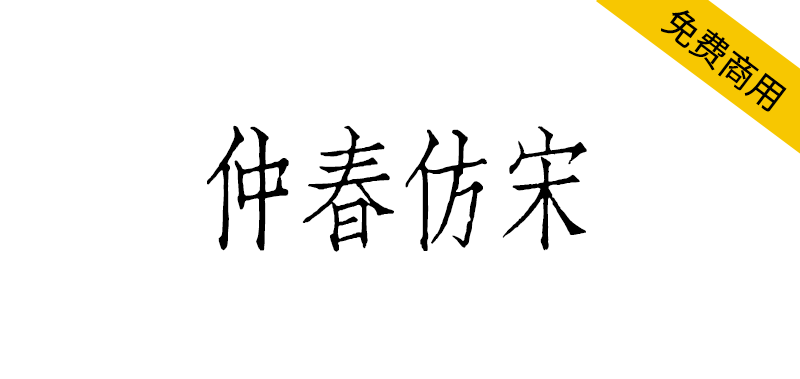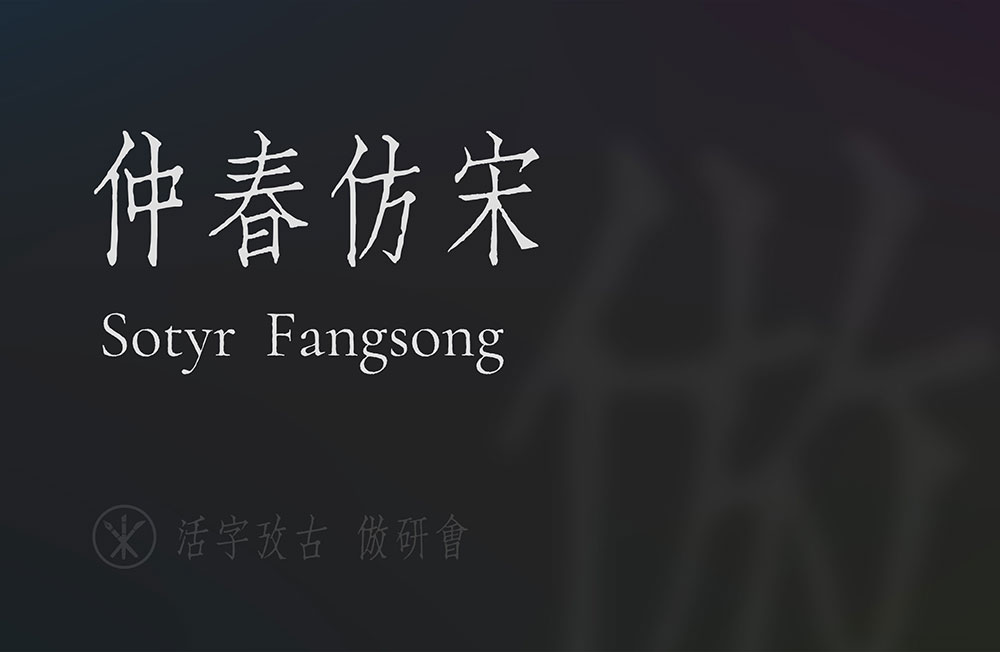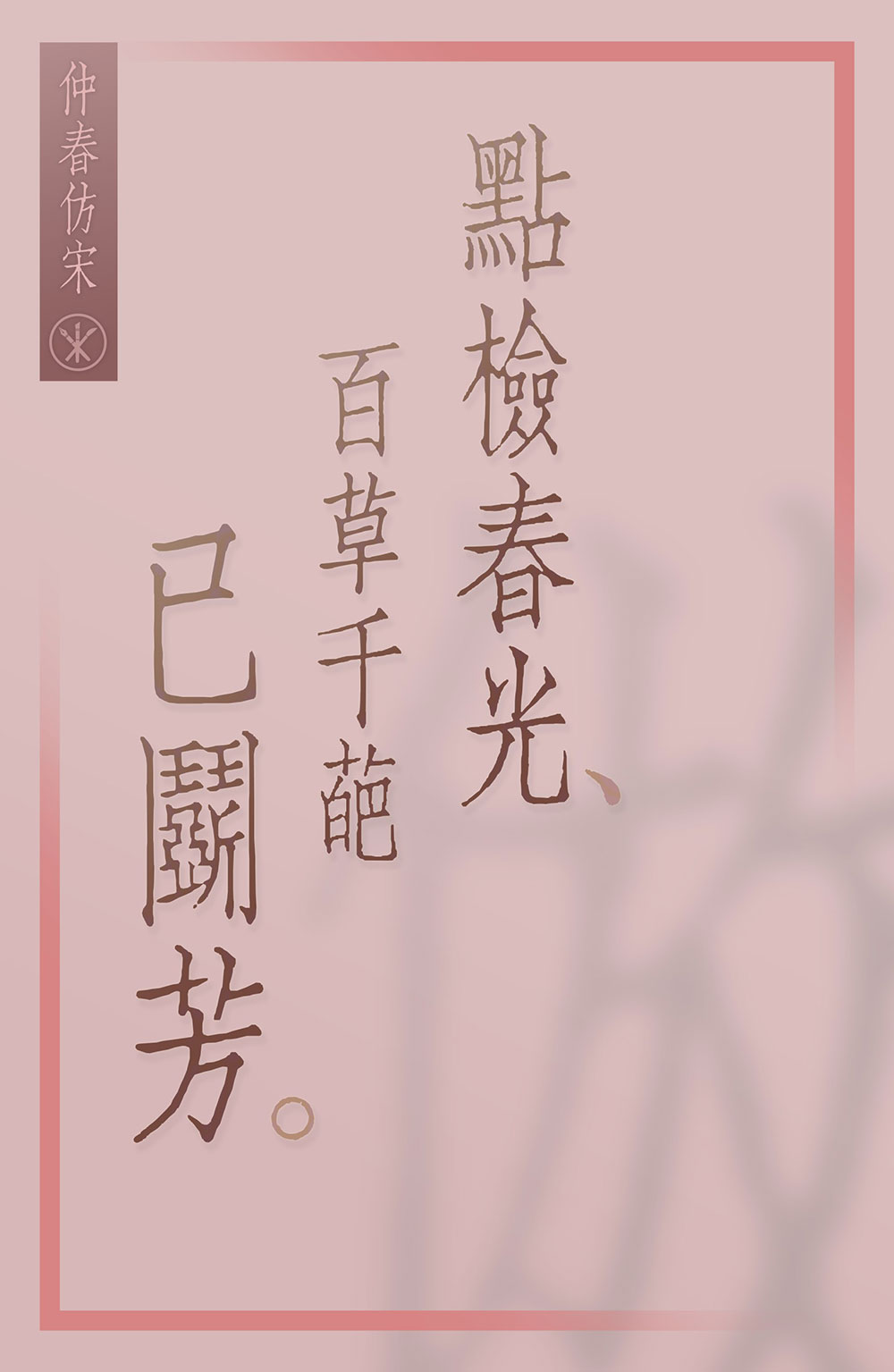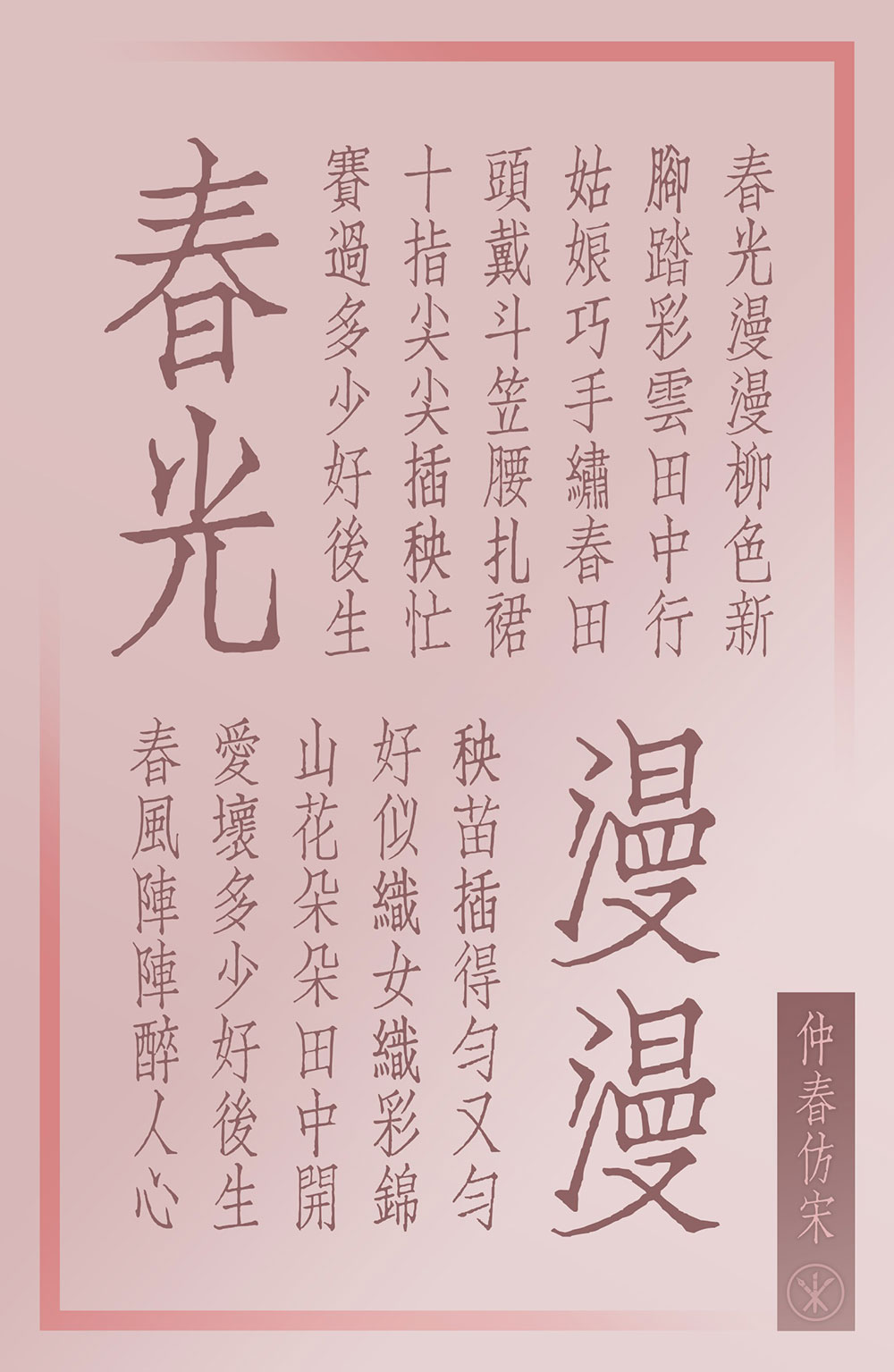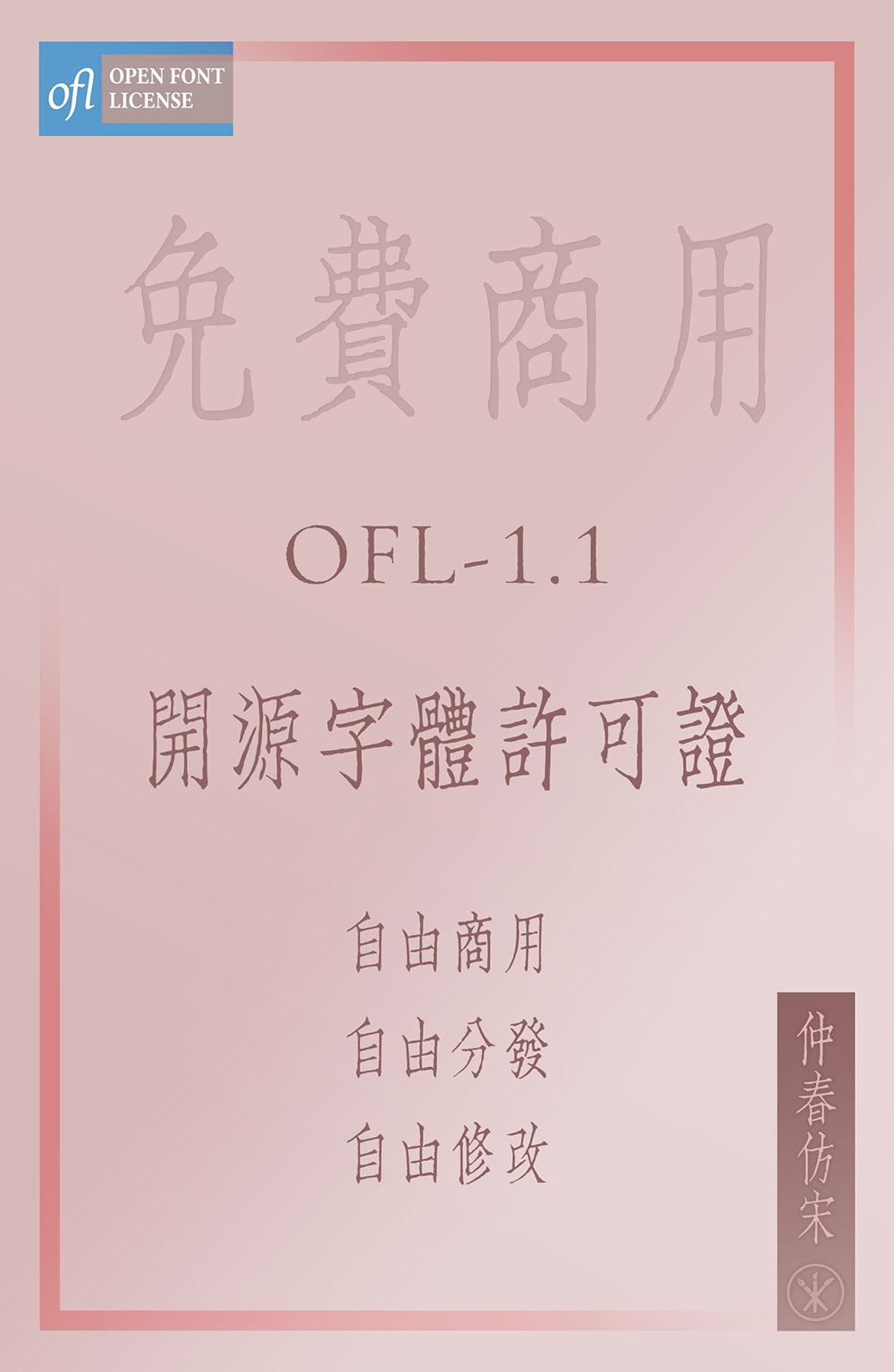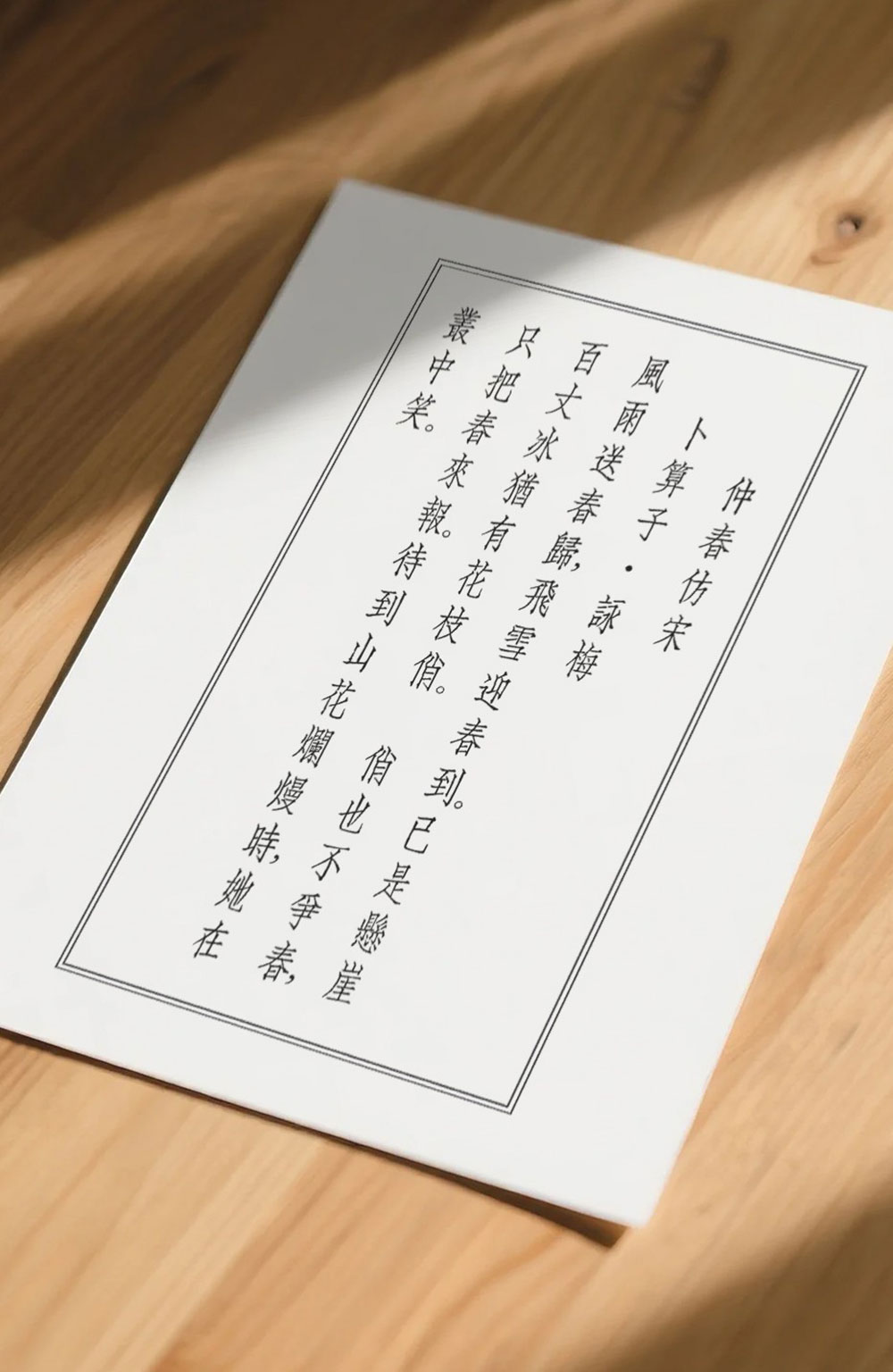
仲春仿宋(Sotyr Fangsong)项目是对上世纪聚珍仿宋二号长体铅活字字形进行的数字化。采用直接复刻办法,从印刷品扫描件中提取字形并封装为字体。
项目尚处于开发和测试阶段,其中的缺字、丑字不少,远不及正式版发布的程度。简化字部分是基本没有的,也不太推荐用于现代汉语文本的排版,还请各界朋友多多包涵。
开发故事:若论哪套长体仿宋最为著名?熟谙近现代印刷史的同志,恐怕大都会脱口而出「聚珍仿宋」。不过聚珍仿宋的长体铅字自身又包含多种字号,哪一种最具代表性?这个问题的答案或许在同志们的脑海中能浮现出,但落实到具体字号层面,就不那么好回答了。
聚珍仿宋二号长体铅字,造型妍美多姿,而又因其字号适中,常应用于正文排版而不是标题和夹注。相比于头号字的直健、三号四号字的间架异化处理、五号字的细密,二号字的字形可以说是最丰富地展现了聚珍仿宋家族的风味。同时,上世纪末,聚珍仿宋二号长体经过史云鹏的大力推广,成为了工程类制图常用的手写体。工科出身的朋友们,你们当年有没有练习过呢?
聚珍的头号方体长体、二号方体,市面已有产品,而尚无二号长体产品可用。
在印刷品样本方面,现在开放的电子化扫描件非常多了,缺少的只是对其中的字形进行提取封装的工作。这个工作量不小,所以从今年(2025)1 月开始,我们又合作开发了一种切片工具和一种封装前处理工具,效率大为提升,小组内的同志们拊掌称奇。
总之,「仲春仿宋」是传统汉字美学、印刷和数字化技术、新生产力结合的产物。
问:「为什么要叫『仲春』」呢?
答:这个项目是乙巳年仲春开始进行的。此外「仲」有「排行第二」的意思,而「春」的声符「屯」又有「聚集」的意思;二者结合,与「聚珍二号」暗应。「Sotyr」是「聚珍」的谐声域。